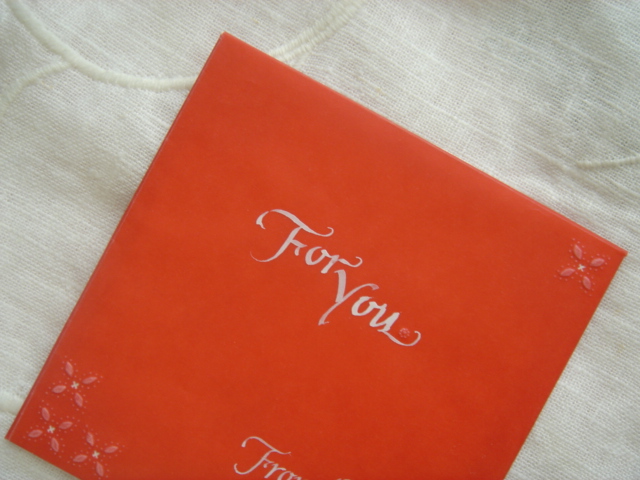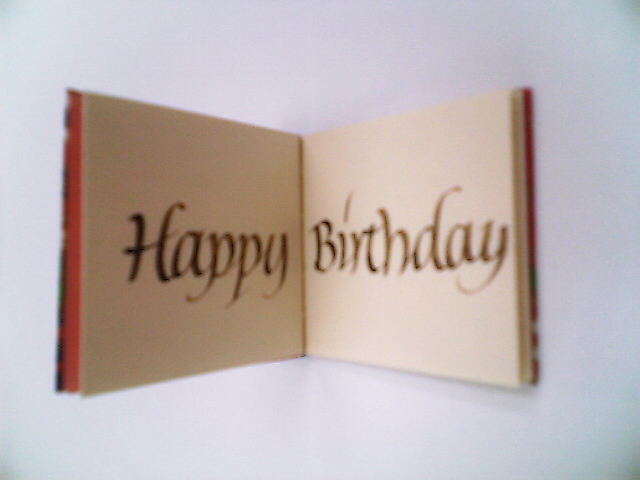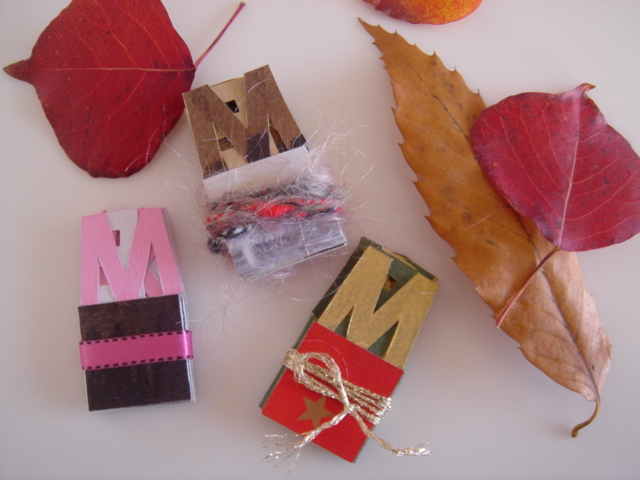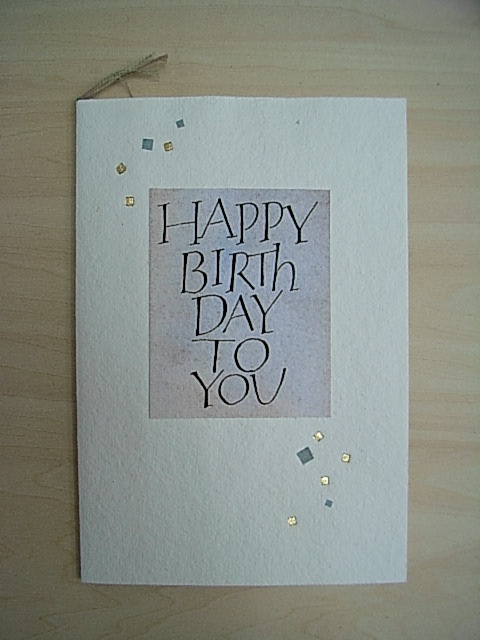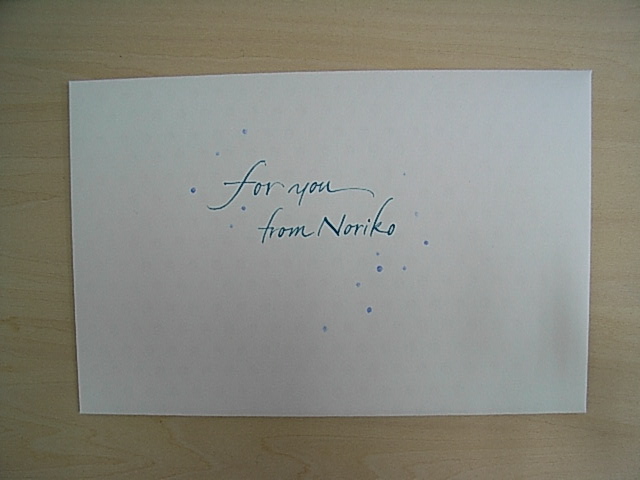
11月のお誕生日カード
12月に突入してしまいましたが、今日はモジトルカードエクスチェンジの11月のお誕生日カードをご紹介します。
今回NEさんにお送りしたカードの作者はYMさん。
アイディアがいっぱいのカードをどうぞご覧ください。
これは外側の封筒。(この写真を撮ったあとに宛名を書きました)
何かかわいいものたちが散らばっています。
この封筒は手作りで半透明紙を上にかぶせた二重のつくり。2枚の紙の間にHappy Birthdayとか
風船とか星などの小さなプレート(金属製かしら?)が入っているのです。
しゃらしゃらっと封筒を揺すってみると…広がってくれました。楽しい仕掛けですね!
カードのおもて側もHappyそのもの。
よく見るとキラキラがいっぱいちりばめてあります。
(これは前に教えてもらった携帯電話を飾るシールでしょうか?)
カードの中をあけると…
今度は優美な美しい色あわせが出てきました。
白い色がマーメイド紙にもきれいにのっています。
最初はこういうふうに折りたたんだカードなのだと思っていたのです。
でも、紙がなんだか厚いような気がしてよく見ると、中にもページがあるではないですか。
そう、これはとっても不思議なカードなんです。
パッと広げると上の画像のように普通に開きます。
ところがカードを両手に持って、左右対称になっている山折部分を互いにくっつけるようにすると中のページが開きます。
説明が下手で申し訳ないです。
が、ホントにポンッと開く…紙が吸い付いてくっつくような感じなのですよ〜。おもしろ〜い!
波形に切ったところに別の色の紙をさしこんであり、裏側(これが中央のページになる)にも文字が書いてあったというわけですね。
たくさんたくさん楽しめる夢いっぱいのカードでした!
「カリグラフィーを愛する友へ」というメッセージに私もうんうんと頷きまして、このカードエクスチェンジ
をやっていてよかったなあと思うのでありました。
作って、贈って、飾って
先週からみなさんと一緒のクリスマスカード作りが始まっています。
今回は飾っても楽しめるものを作りました。
ノイランドで書いて、カットして、下の部分はそれぞれが持ち寄った好きな紙を貼っています。
この紙選びも楽しかったです。
いろいろな色で書いてみました。深いグリーンがきれいに乗って、クリスマスらしい華やかさ。単語と単語の間はあとでリボンをつけてプレゼント箱ふうにする予定のCさん。
落ち着いた色調でまとめたのはhさん。コレクションのクリスマスカードをカラーコピーしたものを使っています。
やわらかめのグリーンの文字と、クリーム+ゴールド系でまとめた上品なカードを作ったのはHさん。
金色のガッシュにトライしたのは、カリグラフィーが初めてのNさん。
貼った紙はペーパーナプキンなので、柔らかい紙のやさしさが出てとてもすてきでした。
幸せを運んでくれるピンクです。雑誌やリーフレットからピッタリの写真を見つけるのが上手なmさん。
Kさんのカードは真ん中のツリーがポイントに。ラッピングペーパーのほかに雑誌広告からもいい色や柄を切り取って。
色数を絞り、下にはmerry christmasの文字を切り取って貼ったsさん。斜めから見るとつながって読める、グッドアイディア。
ブルー系のラッピングペーパーから気に入った模様を探します。文字はくっきりと赤で書いたkさん。
文字は5ミリ幅のペンで。この書体はペンアングルが0度と90度の組み合わせ。カーブのところはちょっと苦労です。
マーカーで書くとラクです。書けなくなったマーカーに絵の具をつけて使ってみました。
たたむととても小さいので「これはいったい何?」状態に…
だからおしゃれにラッピングしてプレゼントしてくださいね!
出てきたものは?
北見都さんから、とってもおしゃれなカードをいただきました。
彼女のアイディアと愛にあふれたカードをご紹介するのが
もう、私の生きがい(?)でして。
11月の今の気分にぴったりの、静かな色のカード…
シンプルでステキです。
何かちょこんと顔を出してるのね、何かしら?
先にメッセージを読むと「ペンにしてみました」って…
そうか〜、金色のクリップがついてますもんね!
カードの切り込みから出てきた、出てきた。
胸ポケットみたいですね。
やっぱり割りピン使われていて、折りたたみになっているのです。
かっこいいペンが出てきました。
金ぴかで高級そうなペン先です。大事にしている万年筆みたい。
しゅるるんるん、と北見さんのようにいい字が書けそうです。
昨日から風邪をひいて、ちょっとショボンとしてましたが
キタミンカード(mojitor-hさん命名)はビタミンカード!
元気になれそうです。
10月の誕生日カード
今月は3枚ご紹介します。
10月がお誕生日のKIさん、RIさん、KYさんおめでとうございます!!
モジトルカードエクスチェンジでは、出来上がったカードは必ず封筒などに入れていただくように
お願いしています。誕生日カードの場合、自分が作ったカードがどなたあてにいくのかはわからないので宛名は「For You」としています。そして、これらの封筒もとってもステキなんです。
そこにも注目してくださいね。
10月という季節にもぴったりのカードです。
淡いグラデーションのウォッシュの上にヴァーサルの
HAPPY BIRTHDAYが調和してきれいです。そのウォッシュと文字
の部分は、厚いカードに貼られており、箔押しとウォッシュと同じ紙がバランスよく配置されています。
そして、カードの折るところには、ウォッシュと同調するグラデーションがきれいなループが添えられています。
全体に、やさしい色と雰囲気のあって、制作者のセンスがひかるカードです。二枚目です。NEさん制作のカードはRIさんへお送りしました。
ブック型のカードの表紙とおそろいの紙が貼られた、おしゃれな
お手製の封筒に入っています。
このブルーの色がなんとも言えず素敵です。(私の好きな色!)
NEさん、この紙自体も、もしかして、手作りでしょうか?
だとしたら、この水玉模様…驚嘆です。
さて、このカードはとってもかわい〜い大きさ、いや、小ささ、なんですよ。
ペン先サイズ!こんな細かい作業を指で?私の太い指じゃ無
理ですねえ。
表紙の角も美しく…
中を開くと、おおっ!小さなhappy birthdayが書かれた紙が。
細やかな心配りを随所に感じる、優しいカードでした。
最後はHKさん制作のカード。こちらはKYさんへお送りしました。
半透明の封筒なの
で、中身がちらっと見えて期待がふくらみます。
封印代わりに紙が貼ってありそれを留めているのはふんわりとした和紙。
出てきたのは筆文字のカード。
周りにコラージュされた柔らかい和紙の色あいが文字を囲んでいて
墨色との対比が美しいですね。
この画像では見えないようにしたんですが、裏にまたまた素敵な文字でお名前が書いてありました。
その上に貼られた、この紙もお手製ですね。このにじみの美しい紙が半透明封筒から透けて見えて、スモーキーな演出をしていたんですね。
どの面から見てもHKさんのセンスを感じることができるカードです。
こんなふうに毎回美しいお誕生日カードを見ることができて、エクスチェンジ担当はとっても得した気分なのです。
ソーイングの秋ですね
家の中に風邪っぴきさんがいると、静かにしているので
たまっていた縫い物なんかをしています。ちくちくちく…
ああ、針目はガタガタだ〜
9月にいただいた北見都さんの割りピンシリーズの新作!
もう、もう、もう!かわいいですよね〜!
ホワホワしたピンクの布地が貼ってあって、本物のピンクッションみたい。
待ち針だってビーズを使った手作りで、こんな待ち針が本当にあったらいいのに、と思うほど。さて、これに合わせて、お裁縫テーマのカードを作ってお返し(たまには?)しようかな、とチマチマ描いていたら、昨日北見さんから、
またカードをいただいてしまいました。
それが、これです。
ホラ、カバーをはずすと、ハサミ、はさみ。
割りピンの威力発揮、ピッタリのカードですね。
ご本人いわく「もはや、カードではない?」
いやいや、名人芸です。秋冬もますますパワーアップされるのでは、と思ってます。
割りピンで下の紙を開くと、いつも温かいメッセージを書いてくださっているので
本当にいつもいつも心が穏やかになるのです。
お裁縫仲間に私のお返しカードも混ぜてもらって記念撮影。
明日のモジトルカードの会ではお会いできないので、送りま〜す。
カード会にご参加のみなさん、北見さん作のカードも交換会に登場ですよ。どうぞお楽しみに。
北見さんのカードと共に…
カード作家の北見さんがくださった潮風の香り…。
そうです、そうです、貝殻…。
そろそろ夏も終わりを告げる頃。
貝殻を耳にあてれば、
海の音…。
やわらかくて、
ふかふかして、
ましろな紙に
まるで砂に書いたような
「How are you」
ここなら波では
消えないね。
四隅のカットワークは、手でカットされているのでしょうか?こんな細かいレース模様が…すごい…
小さなところにもこだわりを持って作られた、RIさんの気持ちが伝わってくるカードです。
こちらは、HNさんへのカードです。作者は、KIさんです。
和綴じの5×4cmくらい(測り忘れてしまい、ごめんなさいm( _ _ )m )のミニサイズの本です。
ページを開いていくと、Happy Birthday Best wishes on your special day!
となります。そして、小さな花と落款も!!!文字は、ウォールナットインクでしょうか?!HKさんもきっとページをめくりながら微笑んだのではないでしょうか〜
小さいのに、とても丁寧な仕立てで作られていているんですよね〜。
カードといっても、このような形体あって、とっても新鮮!!!納得!!!
他の毎月のカードは、中身が見れないので残念ですが、大きさ様々、重いものもあり、いったいいったいどんなのだろうと、毎回とても見たい気持ちでいっぱいになります!